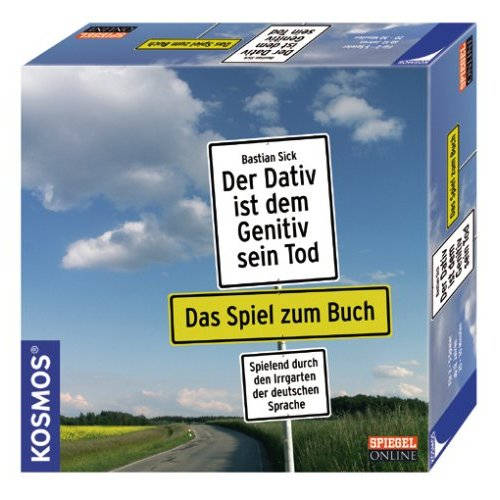
groteske Schriftwahl
ich habe vor kurzem das spiel zum buch (dem dativ ist dem genitiv sein tod)
gesehen und musste wieder innerlich grinsen, da versucht der gestalter die
schilder (orts und hinweis) nachzuempfinden und entscheidet sich für die
INTERSTATE und nicht für die DIN, beide sind schriften für die beschielderung
im einsatz allerdings die INTERSTATE in den usa. ich würde so gerne wissen
wie es zu der entscheidung gekommen ist, ob bewusst – das wäre zu frech
oder unbewusst, nach dem motto – die sieht der schilderschrift ähnlich aus,
das wäre irgendwie witzig und menschlich aber auch schade, sonst sieht man
die DIN so oft und da wo sie passend wäre nicht.
Also auf dem Cover vom Buch sind nur zwei weiße Schilder
zu sehen, die an einer Straße stehen. Die Seitenstreifen der
Straße sind weiß, der doppelte Mittelstreifen gelb. Dies und
die karge Landschaft mit dem Zaun sehen sehr nach USA aus.
Dazu würde dann die Interstate passen. Was dieses Foto mit
dem Thema zu tun hat, weiß wohl nur der (amerikanische?)
Gestalter. :?:
Für das Spiel wurde dann das gelbe Ortsschild hinzugefügt und
das ganze an eine deutsche Straße (Seitenpfosten) gestellt.
Dass die Interstate blieb und dann auch für den zweiten Teil
des Buches für das "Bitte-nicht-stören"-Schild auf dem Cover
benutzt wurde, bringt nur noch mehr Kuddelmuddel in die
ganze Geschichte. :?: :?:
wenn auf dem buch es aber die garamond gewesen wäre?
wie würden die pseudo schilder dann aussehen?
es geht doch um die deutsche sprache,
warum dann auf dem buch die interstate?
ich möchte nicht darauf rum reiten, finde es aber einfach witzig.
... und das, weils auf dem Buch auch so ist ...
und gerade bei dem ersten ist es doch das gleiche was ich sagen will.
Die Interstate passt schon zur Landschaft. Es ist eine Straße in den
USA. Da hätte die DIN auch wieder nicht gepasst. Das Foto auf dem
Cover vom ersten Buch ist meiner Meinung nach der Ursprung für
den ganzen Murks.
das glaube ich nicht, dass jemand das foto als amerikansich eingeordnet
hat und deswegen die interstete genommmen hat. wenn es so war
dann ist das noch lustiger, schließlich geht es um den inhalt und nicht
um das foto auf dem cover.
Bin ganz Deiner Meinung. Der Gestalter hat sich möglicherweise
nicht sehr viele Gedanken gemacht, ob und wie Foto und Schrift
zum Thema passen. In der Schule würde man sagen:
Themaverfehlung. :(
Würde mich nicht wundern, wenn der (Erst)Gestalter in den USA sitzt.
Wenn man nur mehr erfahren könnte...
mich schon, warum sollte ein verlag aus dutschland in usa gestalten lassen?
ist es etwa billiger ;-)